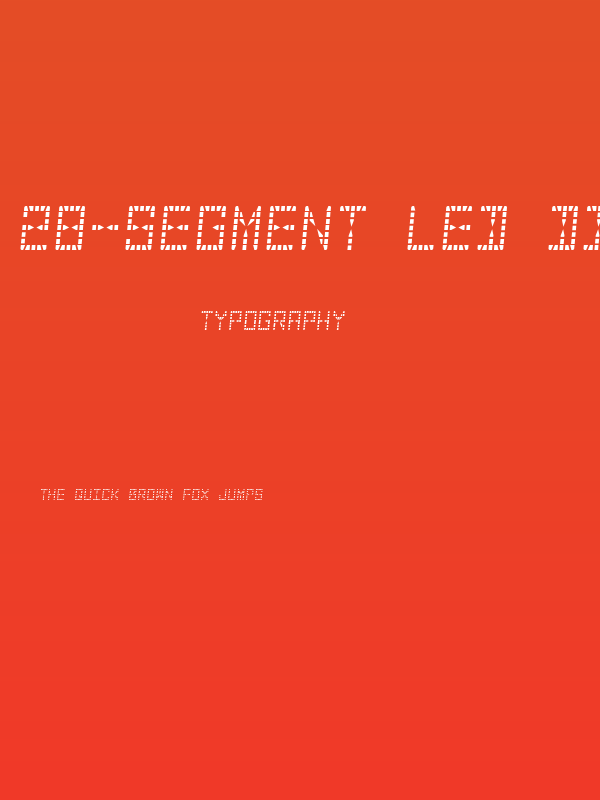
28-Segment LED DisplayRegular Font
| 使用场景 | Headlines, Logos, Digital displays |
| 推荐项目 | Ideal for digital interfaces, tech-themed designs, retro-futuristic projects, and any application requiring a digital or mechanical aesthetic. |